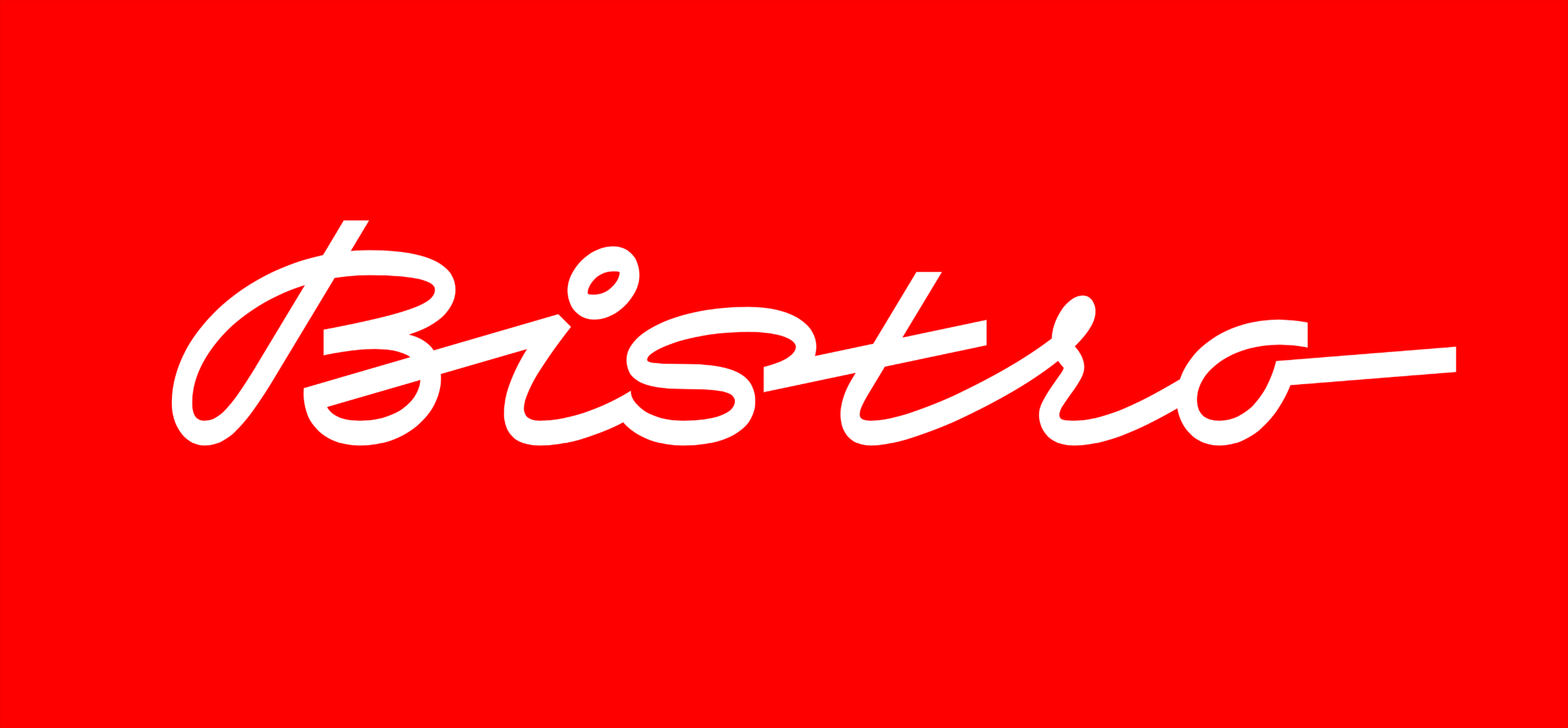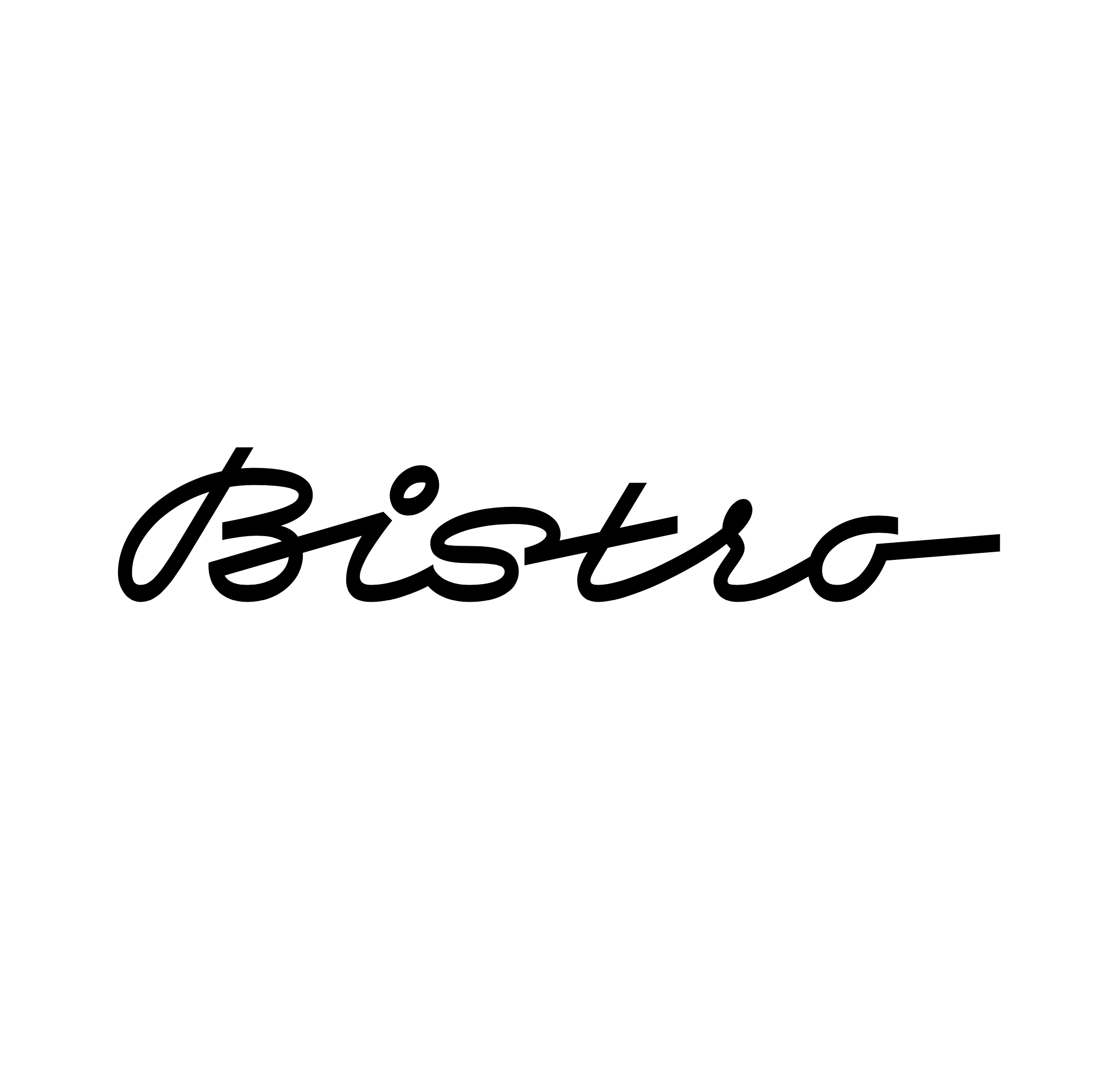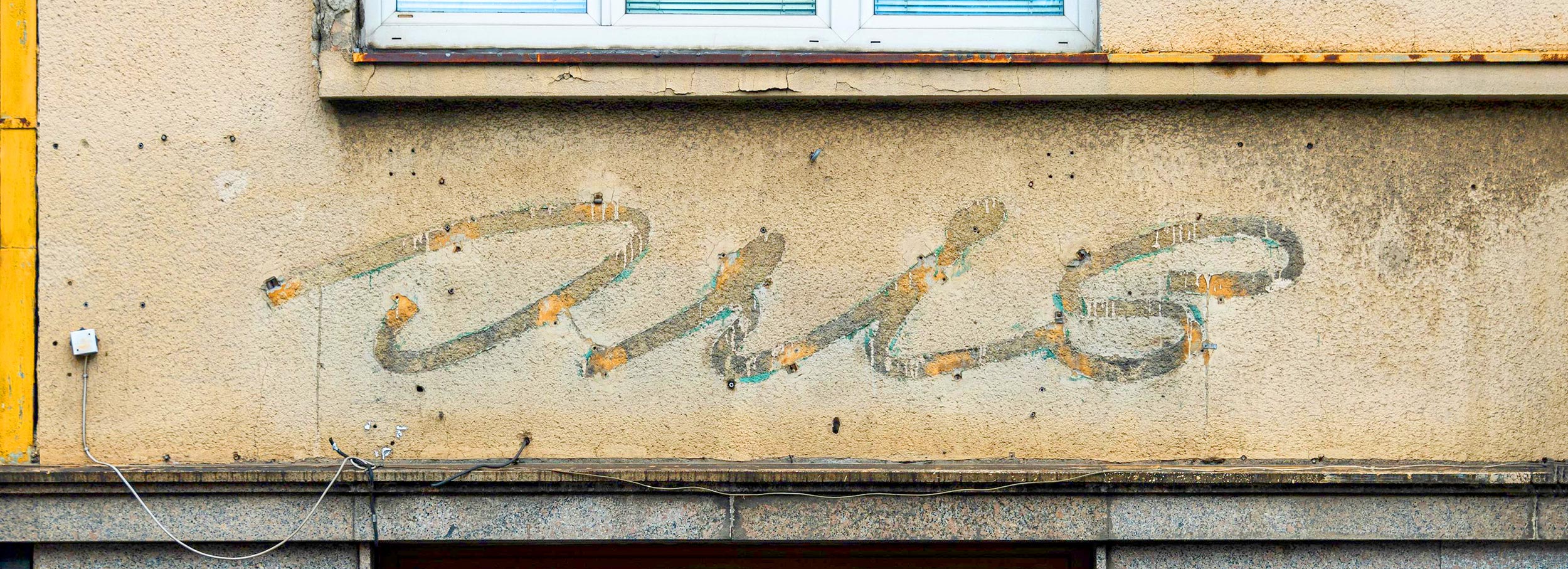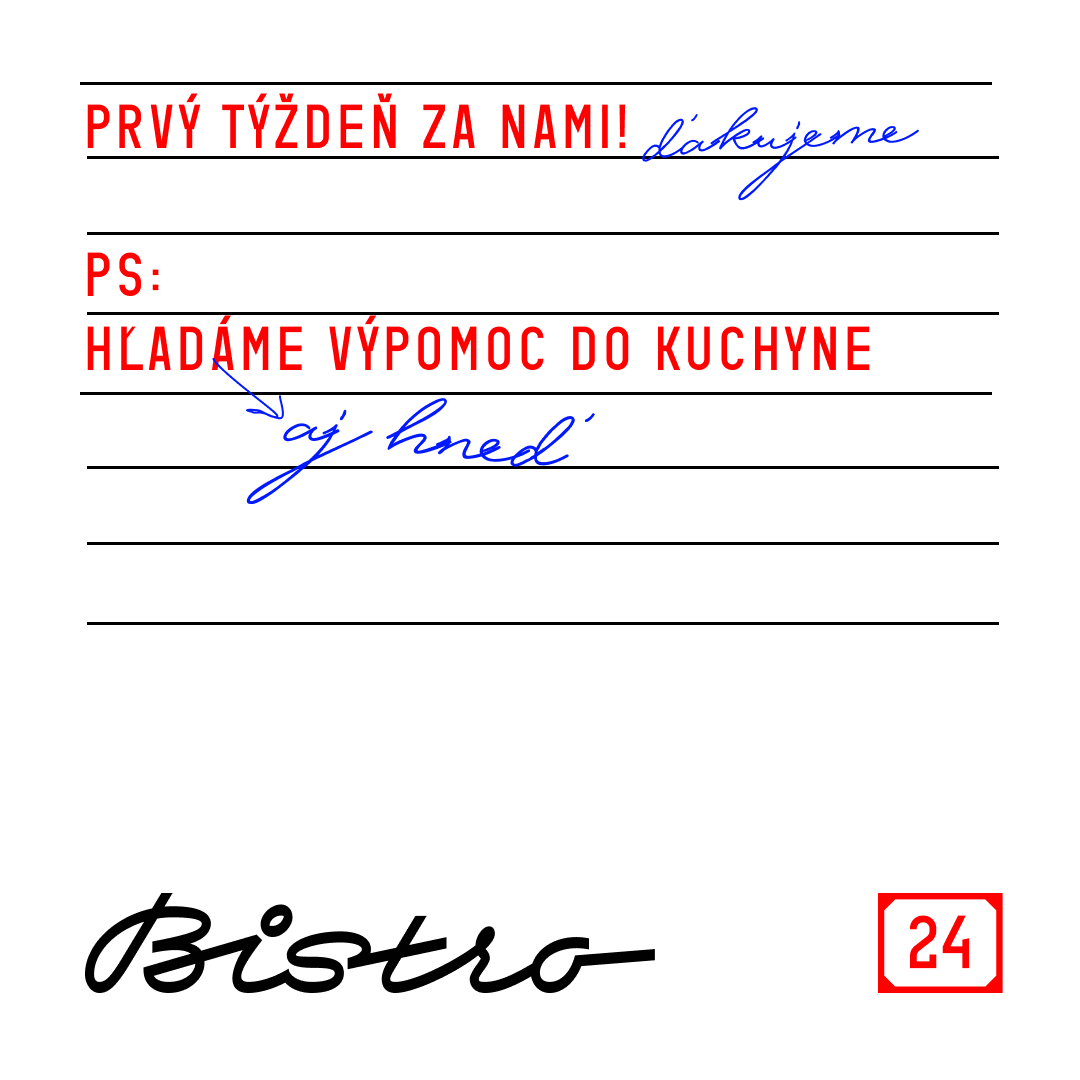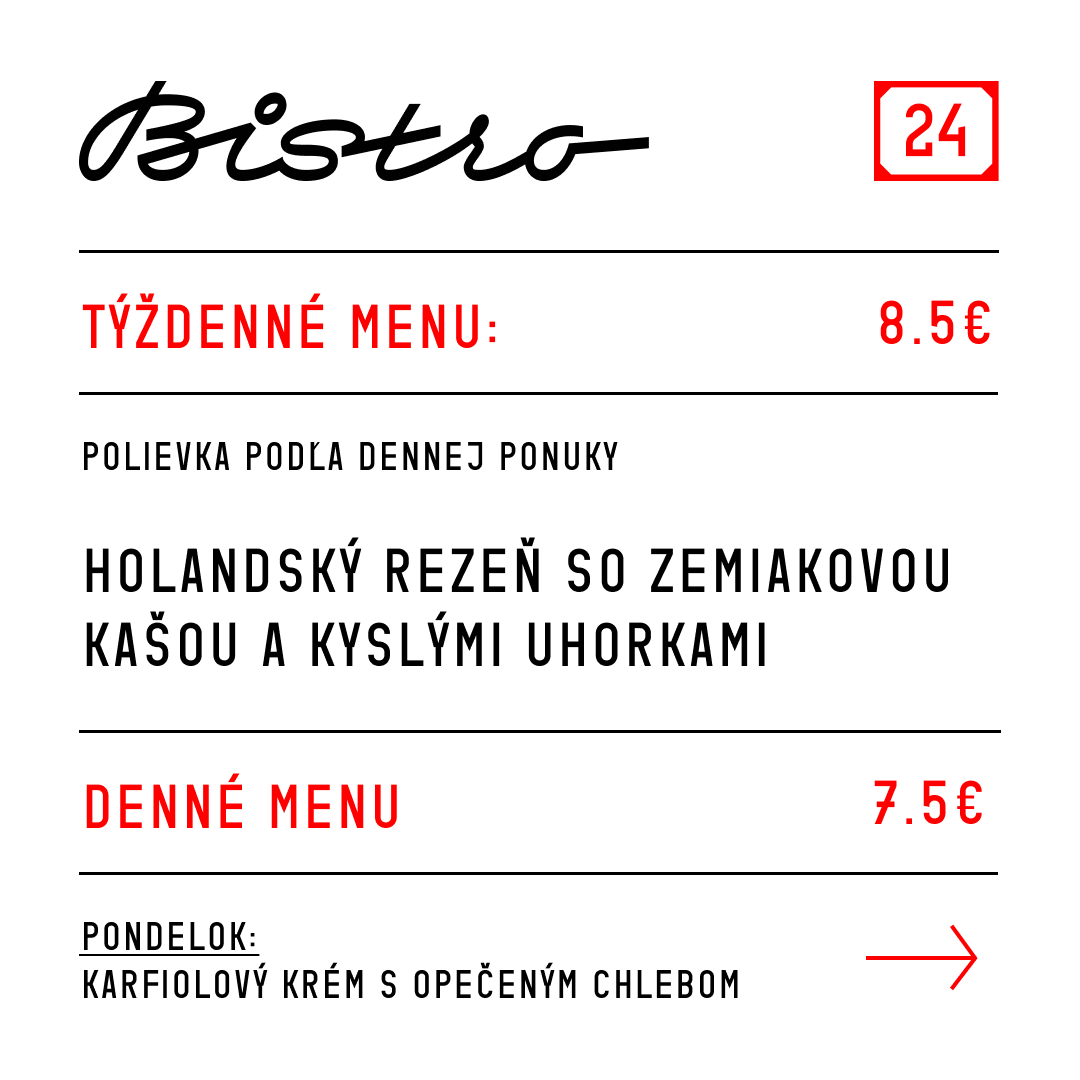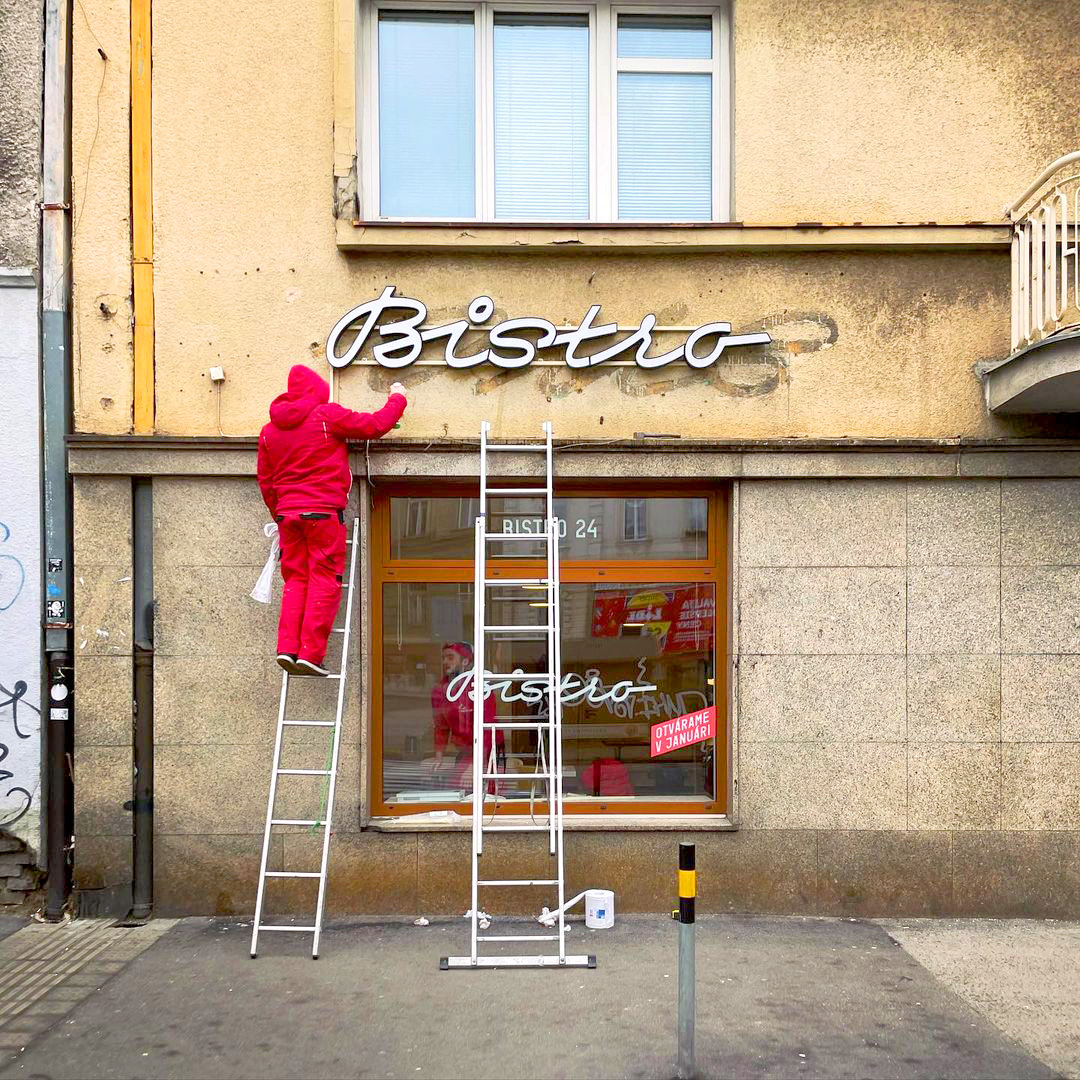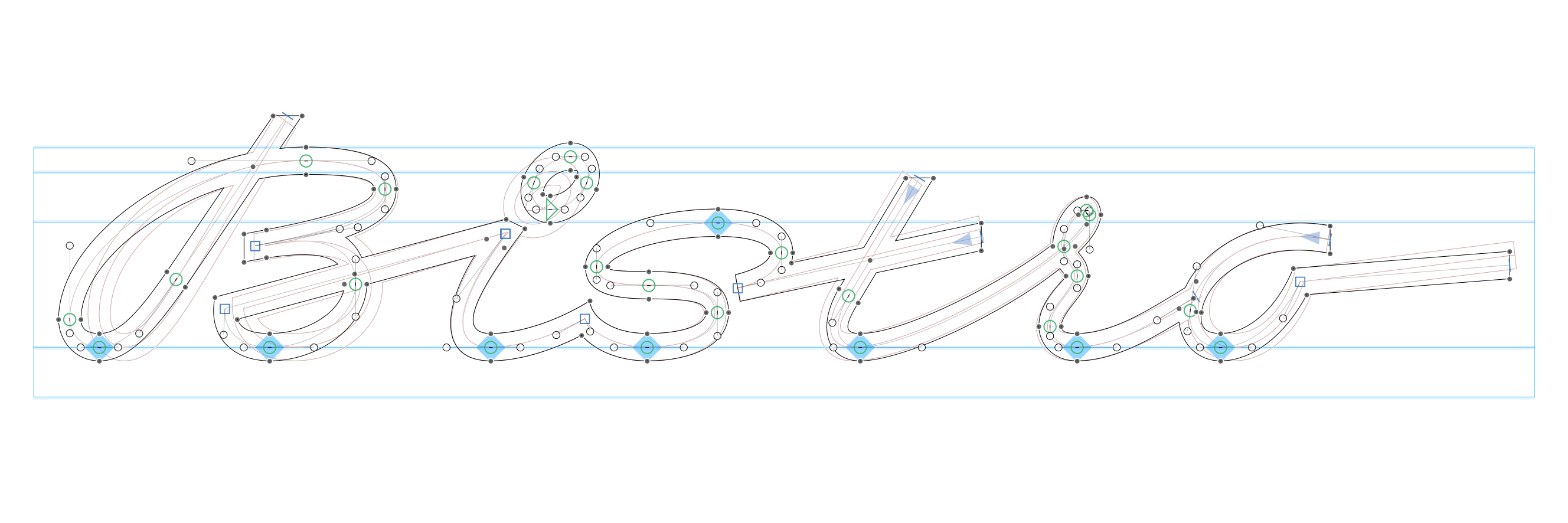
Bistro 24
Spojitý písaný lettering s inverzným kontrastom pre bistro v Bratislave inšpirovaný nápisom „Iris“, ktorého kontúry ostali viditeľné na fasáde po pôvodnej prevádzke.